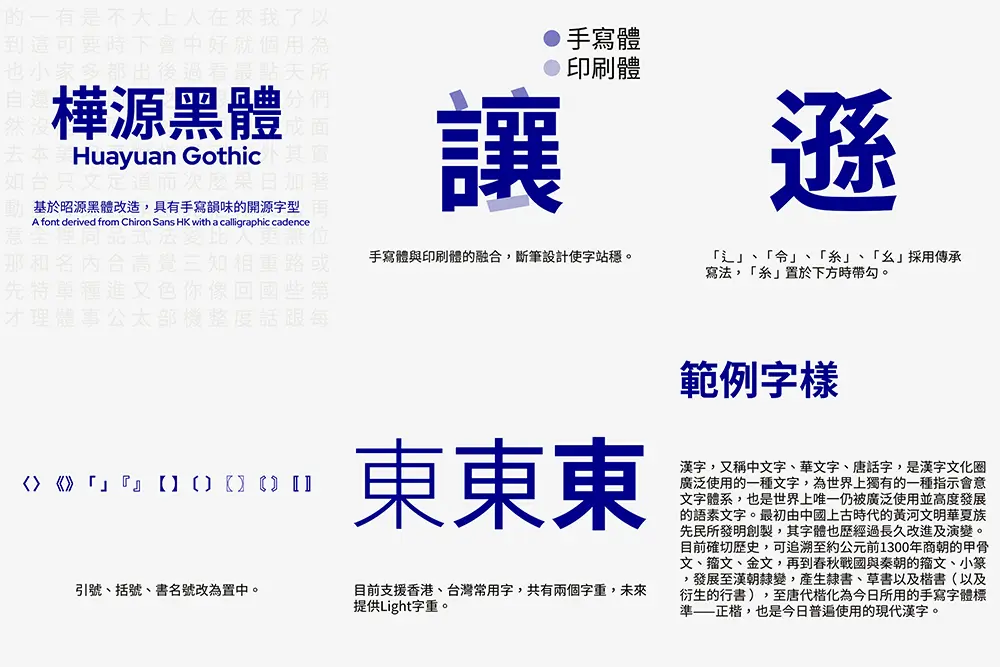
樺源黑體是一套基於昭源黑體、思源黑體改造,融合手寫韻味的開源字體。部分字形取自臺北黑體。目前支持香港、臺灣常用字,共有兩個字重,未來提供Light字重。
Huayuan Gothic is a font derived from Chiron Sans HK and Source Han Sans, and integrates handwritten and print features in its design. Some characters are taken from Taipei TC Sans. Currently common characters for Hong Kong and Taiwan are supported, and there are two weights, Regular and Bold. Light will be released in the future.